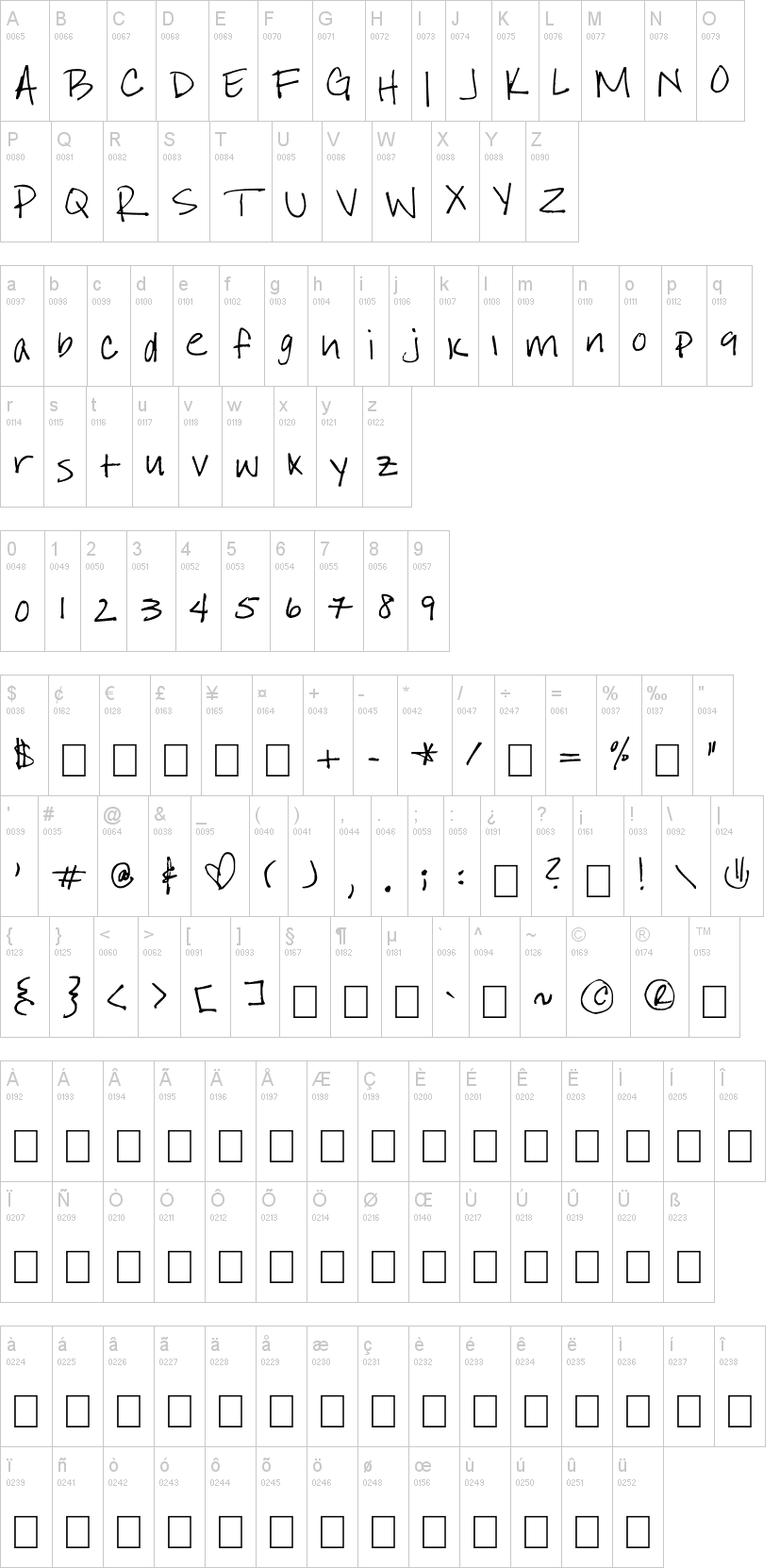
I Still Believe
I Still Believe字体是一款美式手写体字体,由比利时设计师Raymond Larabie创作。它具有浪漫而优雅的风格,在整体外观上充满了活力,拥有温暖的色调,而且更具有艺术感。I Still Believe字体可以用于多种电子媒体,如印刷品、网站、平面设计、电脑桌面等,适用于各种不同的场景。
I Still Believe是一款非常不错的手写艺术字体,具有很好的视觉感,适合于文化类的宣传设计、商业类品牌的广告和产品包装设计以及个性化文字排版等较多场景。